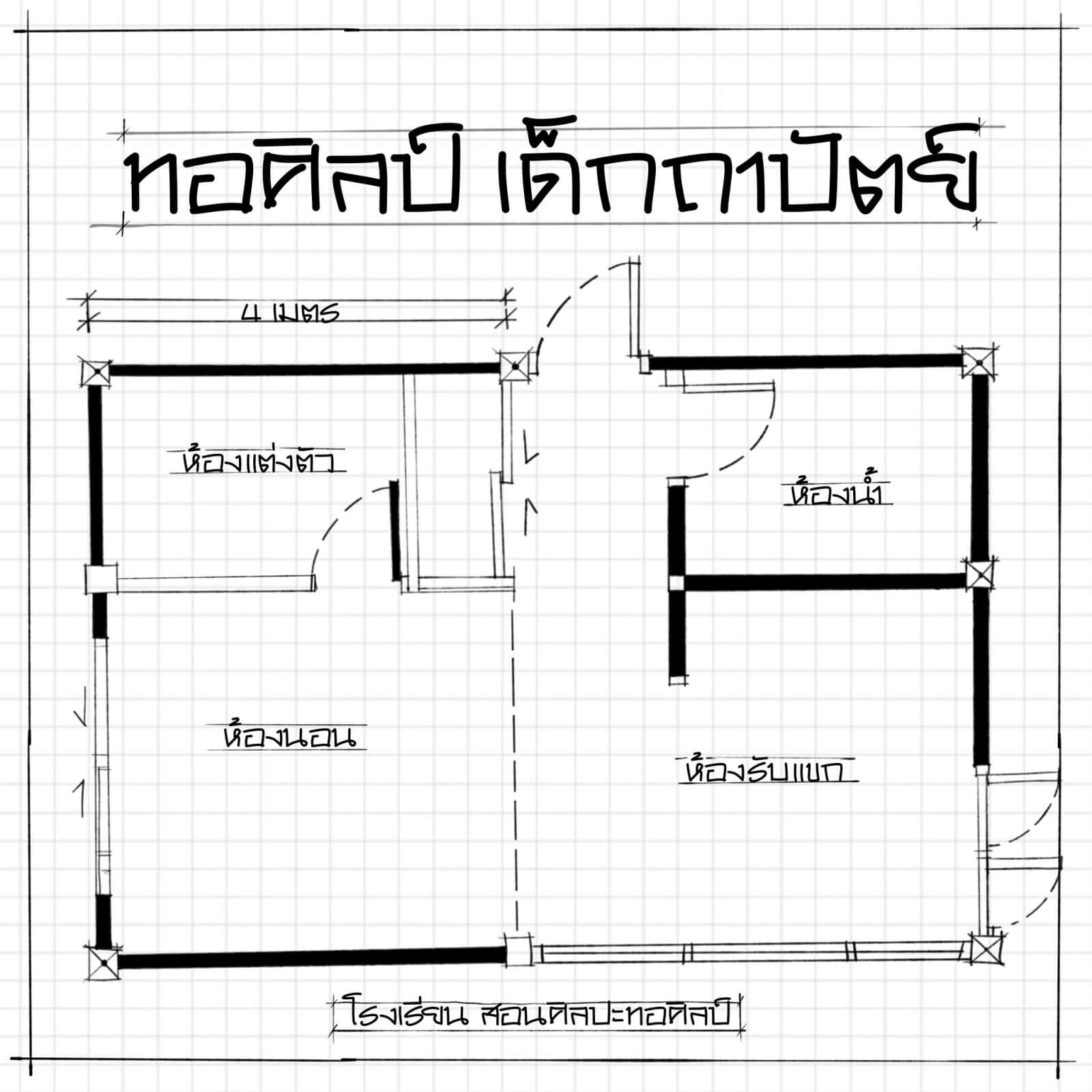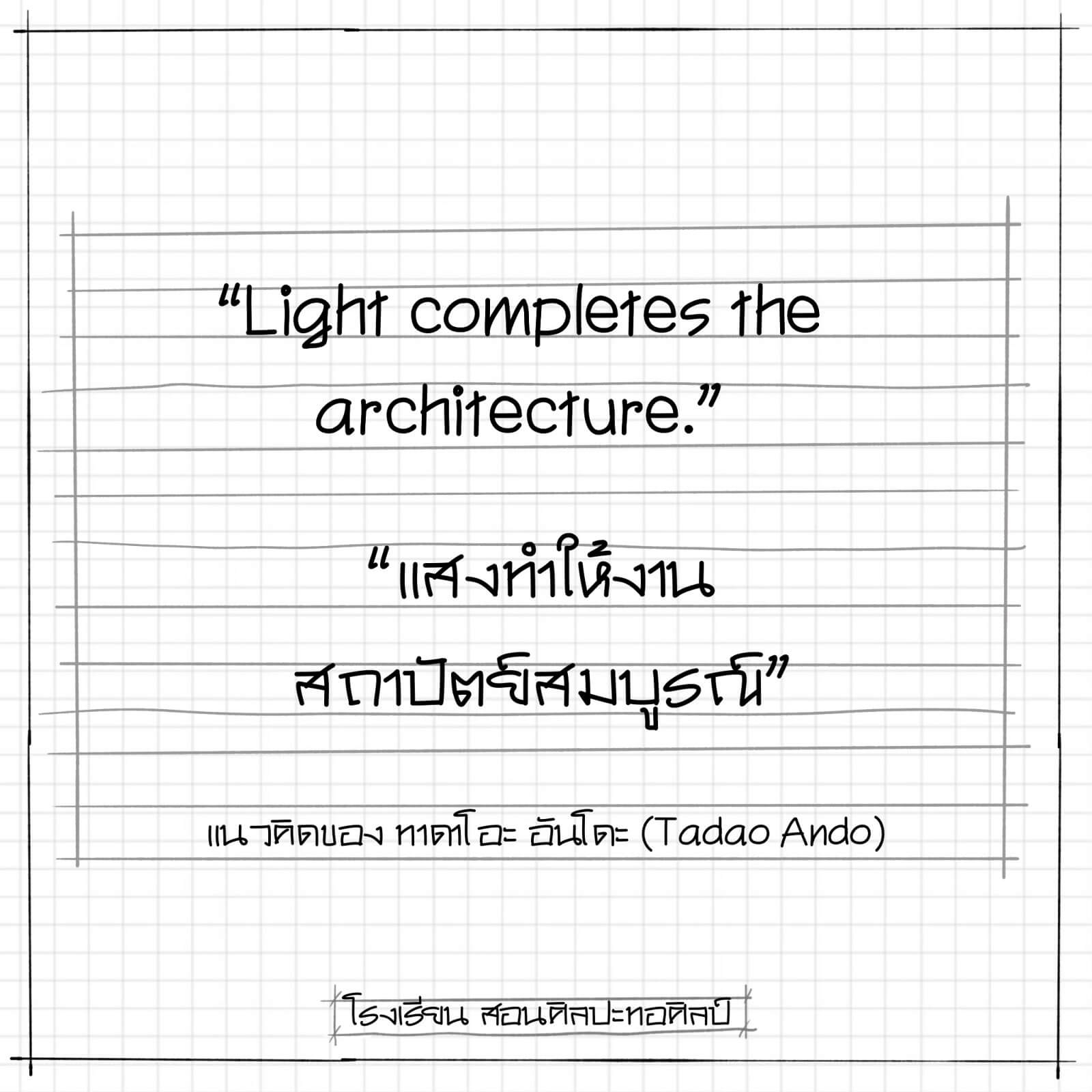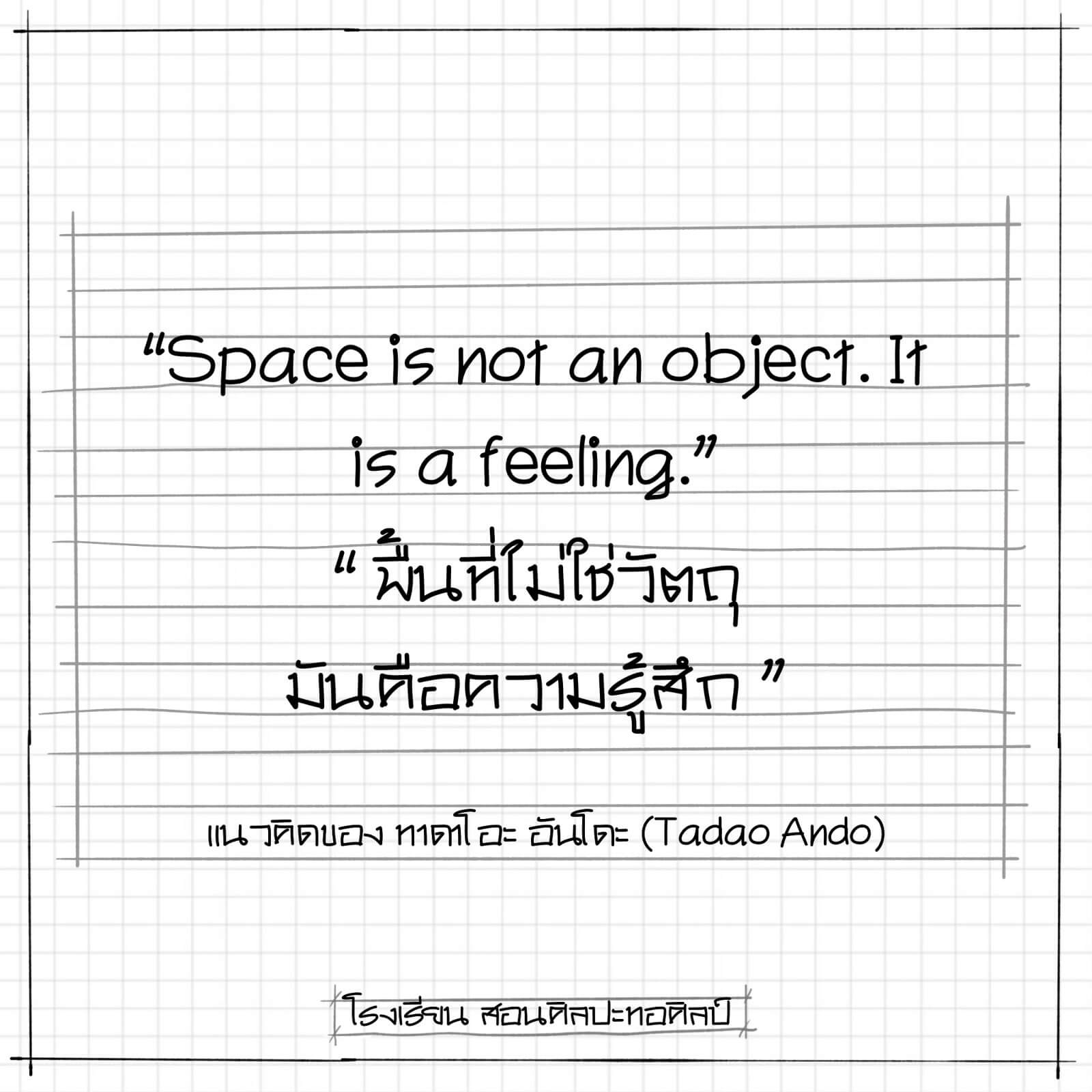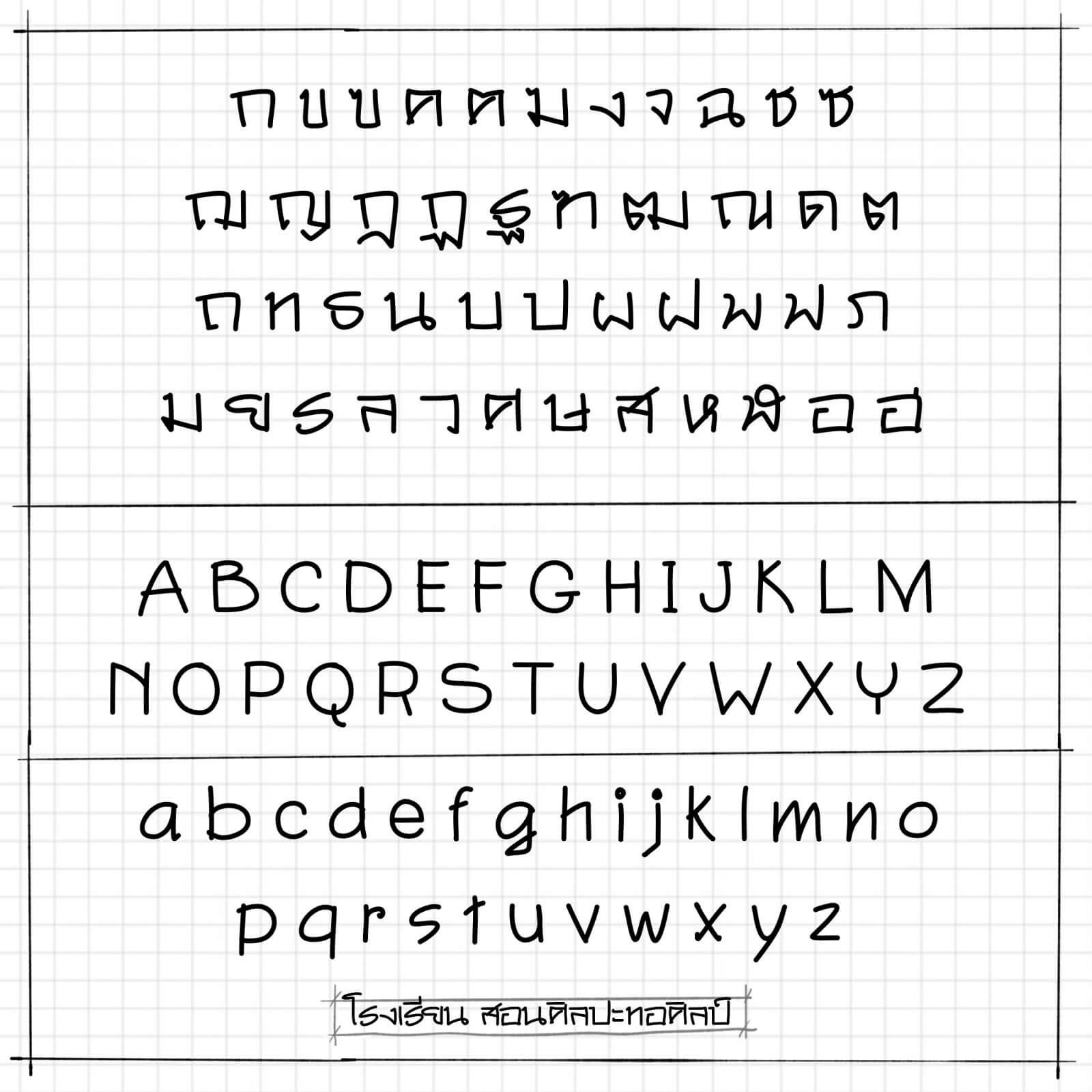
เป็นฟอนต์ที่ทำค้างไว้สักพักหนึ่งแล้ว เป็นลายมือหัดคัดตอนอยากเรียนสถาปัตย์ ตอนหลังถอดใจ ไม่เรียนแล้ว แต่ลายมือยังคงเหลืออยู่ เลยเอามาทำเป็นฟอนต์แจกให้ใช้ฟรีครับผม
ทอศิลป์ เด็กถาปัตย์ (Torsilp Dekthapud)